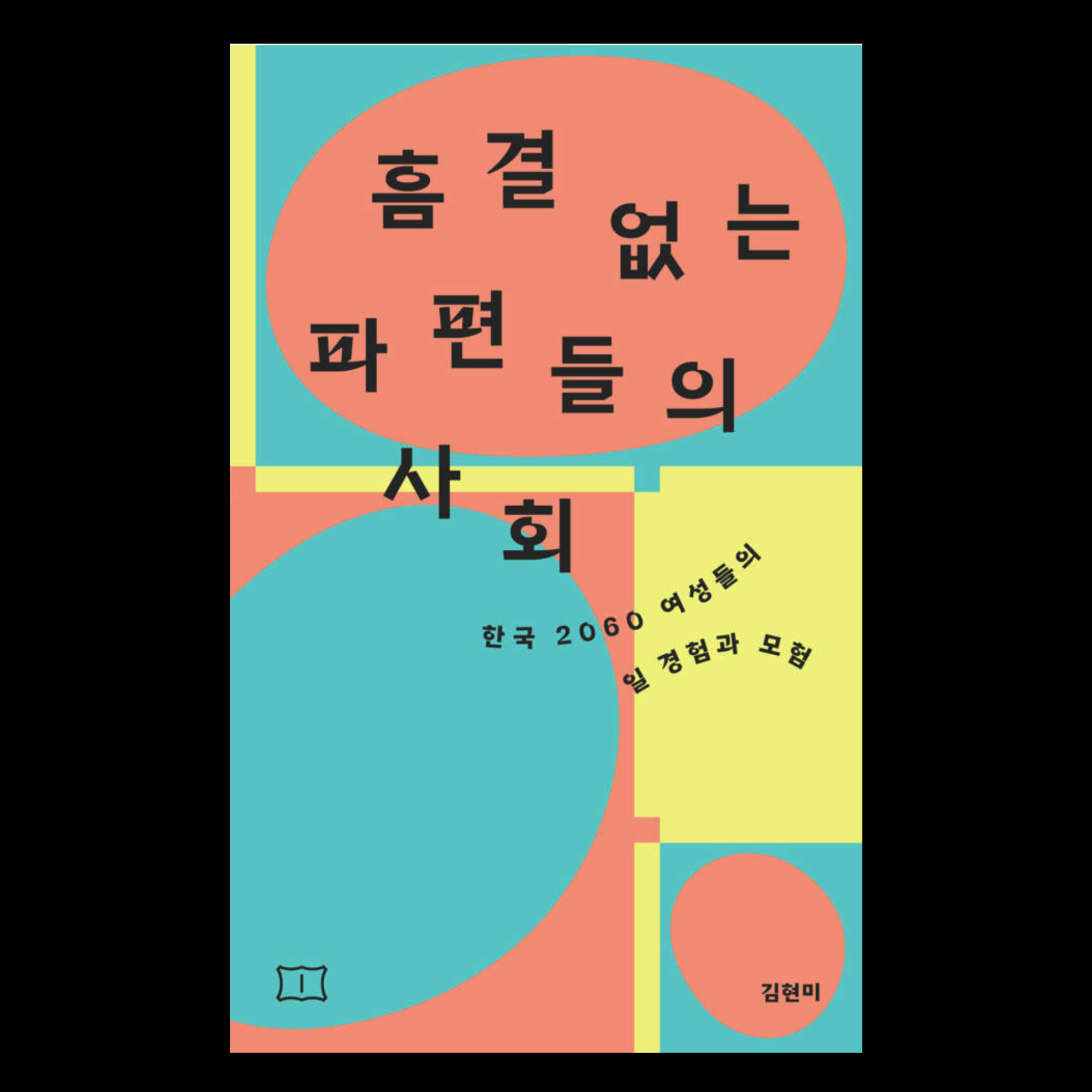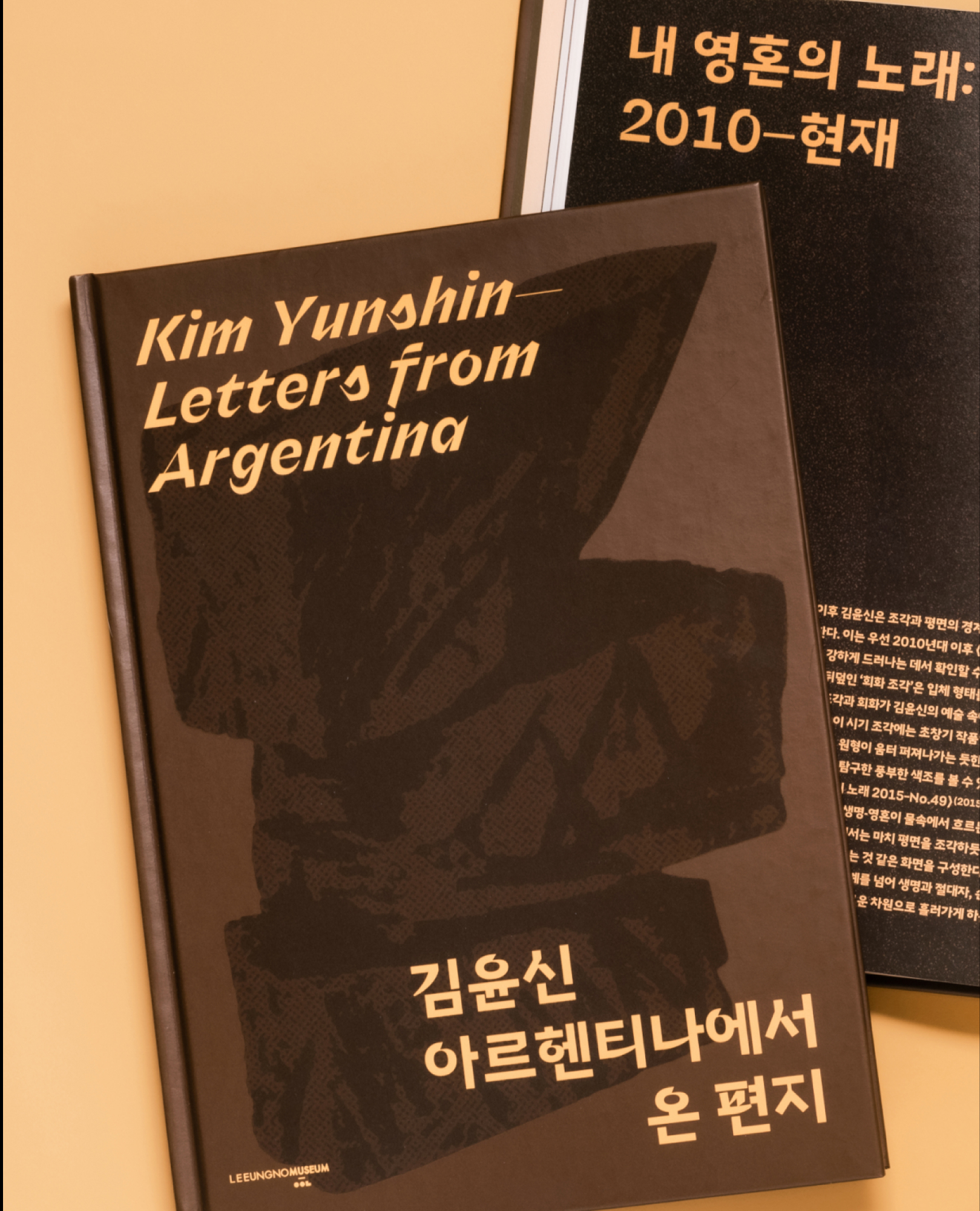
‘오흐탕크(Ortank) 한글 텍스트 / 디스플레이’는 지오매트릭 그로테스크 계열의 서체로 기하학적 형태의 한계를 탐구한 결과물인 오흐탕크 텍스트(Ortank Text), 오흐탕크 디스플레이 (Ortank Display)의 한글 버전입니다. 직선형 그로테스크 스타일에서 오는 약간의 고전적인 느낌에 단순함이 결합되었습니다.
‘오흐탕크 (Ortank) 한글 텍스트 / 디스플레이’는 지오매트릭 그로테스크 계열의 서체로 기하학적 형태의 한계를 탐구한 결과물인 오흐탕크 텍스트(Ortank Text), 오흐탕크 디스플레이 (Ortank Display)의 한글 버전입니다. 직선형 그로테스크 스타일에서 오는 약간의 고전적인 느낌에 단순함이 결합되었습니다. 서체는 큰 단락 형식뿐만 아니라 작은 텍스트까지 여러 종류의 콘텐츠에서 사용이 가능합니다. 디지털 느낌의 오흐탕크 텍스트는 어느 크기에서든 알맞게 가독성을 최대한 유지합니다. 디지털 느낌의 파격적인 디자인을 지닌 오흐탕크 디스플레이는 굵기가 커질수록 디자인 의도가 더 선명하게 드러납니다. 디스플레이만의 독특한 모양들을 체험해 보실 수 있습니다. 오흐탕크 텍스트 / 디스플레이 글꼴가족은 각각 9종(Thin, ExtraLight, Light, Regular, Medium, SemiBold, Bold, ExtraBold, Black)의 굵기들로 구성되어 있으며 가변 글꼴(축: 굵기, 광학크기)도 별도로 제작해 사용범위를 확장했습니다. 새로운 매력을 지닌 서체, ‘오흐탕크 한글 (텍스트 / 디스플레이)’를 사용해보세요!
서체는 큰 단락 형식뿐만 아니라 작은 텍스트까지 여러 종류의 콘텐츠에서 사용이 가능합니다. 디지털 느낌의 오흐탕크 텍스트는 어느 크기에서든 알맞게 가독성을 최대한 유지합니다. 디지털 느낌의 파격적인 디자인을 지닌 오흐탕크 디스플레이는 굵기가 커질수록 디자인 의도가 더 선명하게 드러납니다. 디스플레이만의 독특한 모양들을 체험해 보실 수 있습니다. 오흐탕크 텍스트 / 디스플레이 글꼴가족은 각각 9종(Thin, ExtraLight, Light, Regular, Medium, SemiBold, Bold, ExtraBold, Black)의 굵기들로 구성되어 있으며 가변 글꼴(축: 굵기, 광학크기)도 별도로 제작해 사용범위를 확장했습니다. 디지털 느낌의 오흐탕크 텍스트는 어느 크기에서든 알맞게 가독성을 최대한 유지합니다. 디지털 느낌의 파격적인 디자인을 지닌 오흐탕크 디스플레이는 굵기가 커질수록 디자인 의도가 더 선명하게 드러납니다. 디스플레이만의 독특한 모양들을 체험해 보실 수 있습니다. 오흐탕크 텍스트 / 디스플레이 글꼴가족은 각각 9종(Thin, ExtraLight, Light, Regular, Medium, SemiBold, Bold, ExtraBold, Black)의 굵기들로 구성되어 있으며 가변 글꼴(축: 굵기, 광학크기)도 별도로 제작해 사용범위를 확장했습니다.